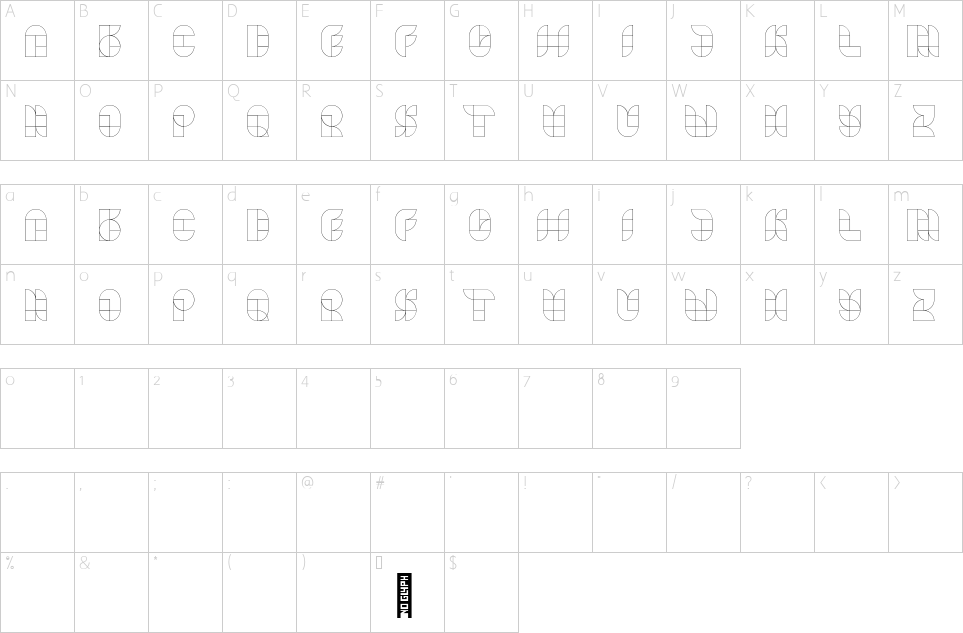
Designkwartier é uma fonte elegante projetada para complementar qualquer projeto gráfico moderno e sofisticado. Oferecida gratuitamente para uso em Windows e Mac, Designkwartier foi criada pelo designer desconhecido atrás desta fonte. Seu design arredondado e elegante combina facilmente com textos de destaque ou se integra bem em materiais online contemporâneos como websites, blogs e redes sociais. Esta fonte é uma escolha ideal para designers que valorizam estilos clean e minimalistas sem abrir mão da personalidade única. Com um download total de 6.971 vezes, Designkwartier mostra seu potencial em projetos variados desde design editorial até logotipos digitais e banners online. A fonte oferece uma variedade de opções de estilo e tamanho que facilitam a sua aplicação em diferentes formatos de mídia digital, tornando-a não apenas versátil como também uma escolha inteligente para designers que buscam recursos gráficos de alta qualidade.